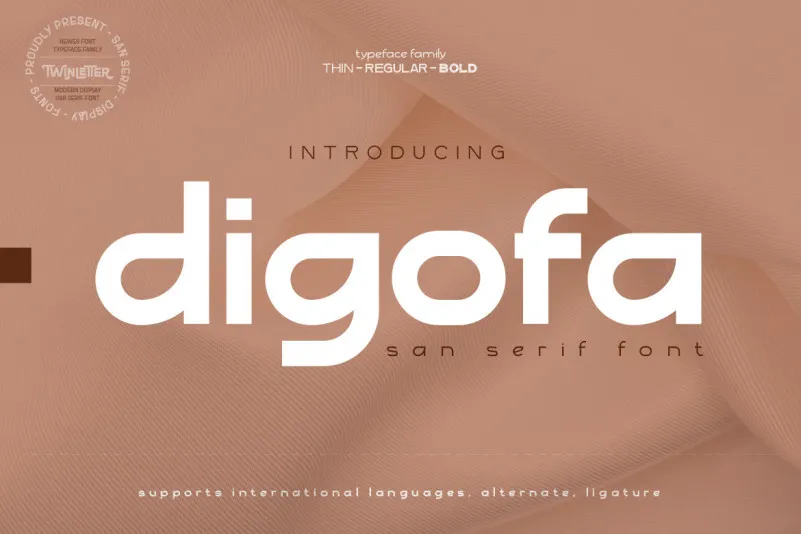
Digofa Font é uma elegante família de fóntes sans-serif criada pelo designer twinletter que oferece beleza natural junto com um moderno estilo moderno. Perfeita para diversas aplicações, Digofa exibe um toque refinado e sofisticado em qualquer design, seja formal ou informal. Suas letras são projetadas meticulosamente para criar uma impressão de elegância e beleza. Esta fonte é adequada para um leque amplo de projetos gráficos, como eventos esportivos, marcações, panfletos, filmes e títulos, rótulos de alimentos e bebidas, tecnologia, slogans, moda e logotipos. Digofa está aqui para tornar seu trabalho de design ainda mais bonito.